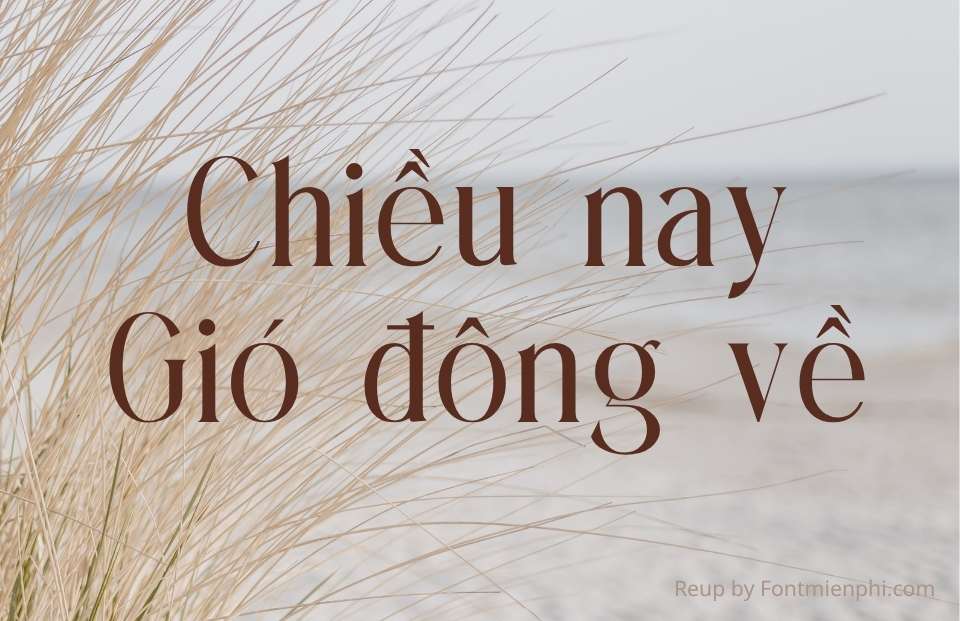
Font Việt hóa 1FTV VIP Eternalo – Nét Đẹp Sang Trọng, Vượt Thời Gian
Một tác phẩm thiết kế đẳng cấp luôn cần đến một bộ font chữ xứng tầm. Nếu bạn đang tìm kiếm sự giao thoa giữa nét đẹp cổ điển và sự tinh tế hiện đại, Font Việt hóa 1FTV VIP Eternalo chính là mảnh ghép còn thiếu cho dự án của bạn.
## 1. Giới thiệu tổng quan về Font 1FTV VIP Eternalo
“Eternalo” mang ý nghĩa của sự vĩnh cửu và vượt thời gian. Đúng như tên gọi, 1FTV VIP Eternalo là một font chữ Serif (có chân) hoặc Sans-serif (tùy thuộc vào đặc tính gốc của phông) được thiết kế với tỷ lệ vàng, tập trung vào sự thanh lịch và mượt mà trong từng đường nét.
Nhằm đáp ứng nhu cầu khắt khe của các nhà thiết kế trong nước, phiên bản Font Việt hóa 1FTV VIP Eternalo đã được ra đời. Các dấu câu tiếng Việt được tinh chỉnh thủ công, chăm chút tỉ mỉ để đảm bảo khi gõ, font không bị vỡ nét, lệch dấu hay mất đi cái hồn nguyên bản của chữ.
## 2. Tại sao nên chọn Font 1FTV VIP Eternalo Việt hóa?
Trong số hàng ngàn bộ font đang có mặt trên thị trường, bộ font VIP này vẫn giữ được vị trí vững chắc nhờ những ưu điểm vượt trội:
### 2.1. Đường nét tinh tế, đẳng cấp
Eternalo sở hữu độ tương phản nét thanh – nét đậm cực kỳ xuất sắc. Các con chữ mang lại cảm giác mềm mại nhưng đầy quyền lực, giúp thu hút ánh nhìn của người xem ngay từ giây phút đầu tiên.
### 2.2. Tối ưu hóa hiển thị tiếng Việt (Kerning chuẩn)
Phiên bản Việt hóa được xử lý kỹ lưỡng về khoảng cách giữa các ký tự (kerning). Các dấu tiếng Việt được đặt ở vị trí hoàn hảo, tương thích hoàn toàn với các bộ gõ hiện tại, giúp designer tiết kiệm tối đa thời gian chỉnh sửa thủ công.
### 2.3. Hiển thị sắc nét trên mọi thiết bị
Dù bạn xuất file in ấn khổ lớn hay thiết kế hiển thị trên các giao diện website, ứng dụng di động, Font 1FTV VIP Eternalo vẫn giữ được độ sắc nét và khả năng đọc (readability) tuyệt vời.
## 3. Ứng dụng thực tế của Font Eternalo trong thiết kế
Sự sang trọng của 1FTV VIP Eternalo giúp bộ font này trở thành “vũ khí tối mật” cho nhiều loại hình thiết kế khác nhau:
• Nhận diện thương hiệu (Branding): Cực kỳ phù hợp để làm Logo cho các thương hiệu thời trang cao cấp, trang sức, spa làm đẹp, khách sạn hoặc bất động sản.
• Thiết kế ấn phẩm truyền thông: Làm nổi bật tiêu đề trên Poster, Banner quảng cáo, Cover Facebook mang phong cách thanh lịch.
• Thiết kế UI/UX Web: Sử dụng làm font chữ tiêu đề (Heading) cho các Landing Page hoặc giao diện website giới thiệu sản phẩm cao cấp, giúp tăng trải nghiệm thị giác cho người dùng.
• Thiết kế thiệp cưới, thư mời: Tôn lên vẻ đẹp lãng mạn, trang trọng cho các sự kiện quan trọng.